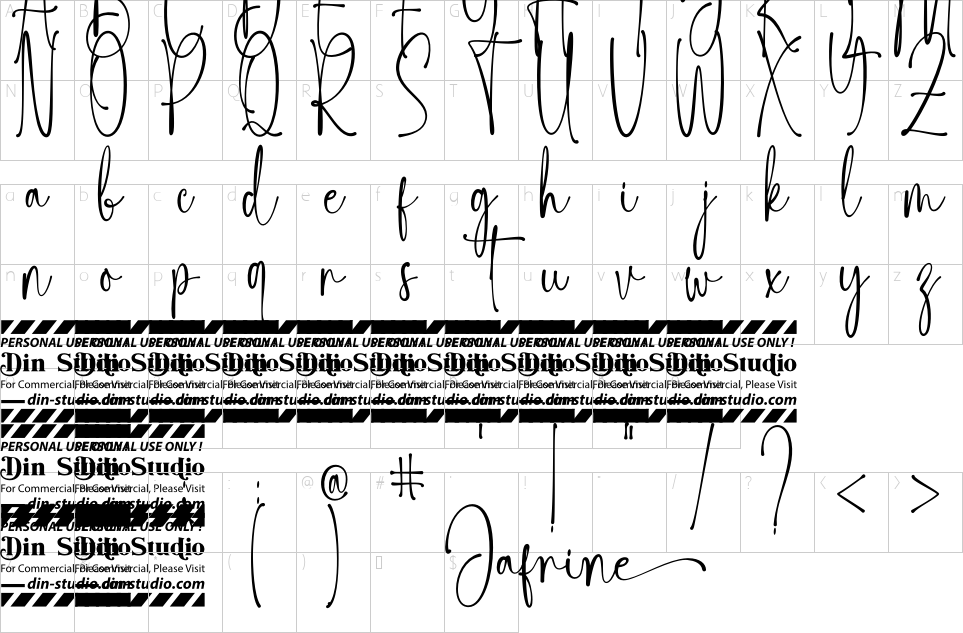
Jafrine Font – Fonte Grátis
Jafrine Font
Descubra a beleza e a simplicidade da Jafrine Font, uma opção de fontes grátis que combina elegância com facilidade de uso. Desenvolvida pela Din Studio, essa fonte foi projetada para criar textos limpos e sofisticados em ambientes digitais diversos. Com seu design minimalista e bem equilibrado, Jafrine é uma escolha perfeita para criações de alta qualidade que se destacam por seu estilo clean. Seja você um designer gráfico ou criador digital, esse recurso oferece a oportunidade de personalizar suas mensagens com estilo, sem comprometer sua qualidade. Com o download gratuito da Jafrine Font, não hesite mais: eletrifique suas criações digitais e impressione seus leitores com uma fonte que complementa perfeitamente seu design. Sem dúvida, essa font será um excelente complemento para qualquer projeto digital que você esteja desenvolvendo.
Mapa de caracteres da fonte Jafrine Font